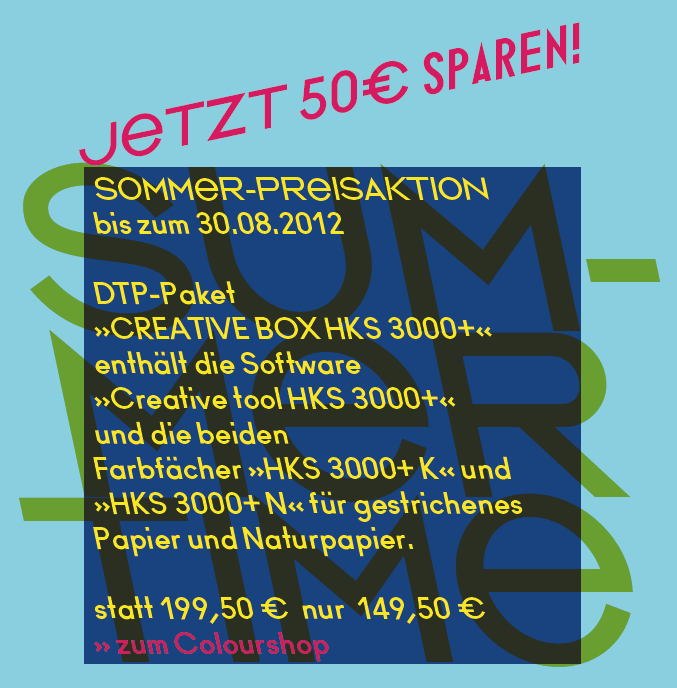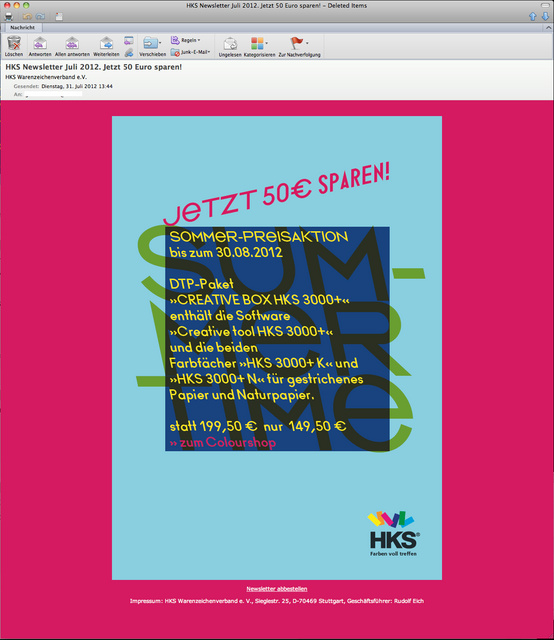
HKS versucht sich in Gestaltung …
Ohne Worte.
»Ich kann doch nicht mein ganzes Praktikum mit Kaffeekochen zubringen. Ich bin doch extra zu Ihnen gekommen, weil ich mal was mit Kreativität und so machen will.«
»Na gut, mach mal die Anzeige.«
Ich gehe davon aus, dass CLMNZ für die Anzeige verantwortlich ist. Zumindest übernimmt er regelmäßig die Gestaltung des HKS-Colourmatch-Periodikums. Er sollte es also wissen.
Gibt es irgendwo eine Hinweis auf den Urheber der Anzeige?
Das war ein Newsletter von heute.
jetzt habe ich Ihn auch bekommen.
die schrift hat ja was. die gestaltung ist typisch 'slanted' hipster style,
die farbmischung ist eher ... brrr und wenn ich ein datum in form
von 30.08.2012 lese läufts mir immer kalt über den rücken.
Wegen der Null vor der Acht?
Klar. Und wegen der fehlenden Abstände.
Welche Abstände?
Ohne Worte.
Ich schätze mal das soll in Richtung „Kunst“ gehen. Anders kann ich mir das gerade nicht erklären. Aber schon schade wenn ein Unternehmen, dass für qualitativ Hochwertiges steht, so schlecht in Erscheinung tritt. Das haben die Farben nicht verdient. :cry:
genau. schrecklich bürokratisch. merkt sich schlechter "war es jetzt der 7.8. oder der 8.7."
sieht doof aus und trägt null (0) infos bei.
ich lass mir sowas ja gefallen wenn es um die reine form des satzes bzw. des rasters geht, ähnlich eines klappzahlenweckers, jedoch nicht im normalen schriftsatz.
Also ich weiß ja gar nicht, was ihr alle habt ...
Lasst euch von einem alten Kartographen sagen:
Linksgeneigte Schrift und blaue Farbe, die es da ja reichlich gibt in der Annonce, passen hervorragend zusammen!
Denn seit alters her werden in topographischen Karten Gewässer (blau) mit linksgeneigter Schrift gesetzt.
In der Anzeige geht es also um irgendwas verwässertes oder um wegschwimmende Felle oder so ...
Also alles gestalterisch wohl abgestimmt ...
Oder so ...
Die Schrift ist grauenhaft! :shock:(meine ganz persönliche Einzelmeinung)
Wenn du erlaubst, schließe ich mich deiner «ganz persönlichen Einzelmeinung» hier dennoch an.
StefanB hat recht – ist z. T. von mir – allerdings hab ich den Text nicht reingefüllt, was die Feintypografie betrifft (Datum). Der Newsletter ist auf der Basis des HKS-Einlegers im Colourmatch gestaltet.
Das Colourmatch 18 ist ja aktuell auch mit dieser grässlichen Schrift verunziert, die von den Gestaltern der Olympiaschrift stammt (Gareth Hague/Alias). Freut mich übrigens, dass ihr den HKS-Newsletter hier erwähnt, und dass die Farben und die Schrift für Diskussionsstoff sorgen.
Thema des Colourmatch 18, das die Grundlage des Newsletters ist, ist »Dictators of Taste« ...